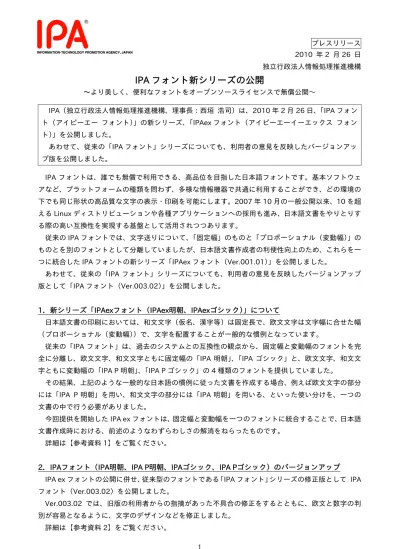
IPA フォント新シリーズの公開
〜より美しく、便利なフォントをオープンソースライセンスで無償公開〜 IPA(独立行政法人情報処理推進機構、理事長:西垣 浩司)は、2010 年 2 月 26 日、「IPA フォン ト(アイピーエー フォント)」の新シリーズ、「IPAex フォント(アイピーエーイーエックス フォン ト)」を公開しました。 あわせて、従来の「IPA フォント」シリーズについても、利用者の意見を反映したバージョンアッ プ版を公開しました。 IPA フォントは、誰でも無償で利用できる、高品位を目指した日本語フォントです。基本ソフトウェ アなど、プラットフォームの種類を問わず、多様な情報機器で共通に利用することができ、どの環境の 下でも同じ形状の高品質な文字の表示・印刷を可能にします。2007 年 10 月の一般公開以来、10 を超 える Linux ディストリビューションや各種アプリケーションへの採用も進み、日本語文書をやりとりす る際の高い互換性を実現する基盤として活用されつつあります。 従来の IPA フォントでは、文字送りについて、「固定幅」のものと「プロポーショナル(変動幅)」の ものとを別のフォントとして分離していましたが、日本語文書作成者の利便性向上のため、これらを一 つに統合した IPA フォントの新シリーズ「IPAex フォント(Ver.001.01)」を公開しました。あわせて、従来の「IPA フォント」シリーズについても、利用者の意見を反映したバージョンアップ 版として「IPA フォント(Ver.003.02)」を公開しました。 1.新シリーズ「IPAexフォント(IPAex明朝、IPAexゴシック)」について 日本語文書の印刷においては、和文文字(仮名、漢字等)は固定長で、欧文文字は文字幅に合せた幅 (プロポーショナル(変動幅))で、文字を配置することが一般的な慣例となっています。 従来の「IPA フォント」は、過去のシステムとの互換性の観点から、固定幅と変動幅のフォントを完 全に分離し、欧文文字、和文文字ともに固定幅の「IPA 明朝」、「IPA ゴシック」と、欧文文字、和文文 字ともに変動幅の「IPA P 明朝」、「IPA P ゴシック」の 4 種類のフォントを提供していました。 その結果、上記のような一般的な日本語の慣例に従った文書を作成する場合、例えば欧文文字の部分 には「IPA P 明朝」を用い、和文文字の部分には「IPA 明朝」を用いる、といった使い分けを、一つの 文書の中で行う必要がありました。 今回提供を開始した IPA ex フォントは、固定幅と変動幅を一つのフォントに統合することで、日本語 文書作成時における、前述のようなわずらわしさの解消をねらったものです。 詳細は【参考資料 1】をご覧ください。 2.IPAフォント(IPA明朝、IPA P明朝、IPAゴシック、IPA Pゴシック)のバージョンアップ IPA ex フォントの公開に併せ、従来型のフォントである「IPA フォント」シリーズの修正版として IPA フォント(Ver.003.02)を公開しました。
Ver.003.02 では、旧版の利用者からの指摘があった不具合の修正をするとともに、欧文と数字の判 別が容易となるように、文字のデザインなどを修正しました。
IPAexフォントシリーズについて
特徴:
(1)固定幅文字とプロポーショナル(変動幅)文字の統合 「IPA明朝・IPA P明朝」および「IPAゴシック・IPA Pゴシック」をそれぞれ一つのフォントに統 合した「IPAex明朝」、「IPAexゴシック」を新規に開発しました。和文文字(仮名、約物4、漢字) は固定幅で、欧文文字は文字幅に合せた幅(変動幅)を基本としたドキュメント用日本語フォント の標準的な実装を行いました。 欧文=変動幅 仮名=変動幅 約物=変動幅+固定幅 漢字=固定幅 記号=変動幅+固定幅 IPA P明朝/ゴシック 欧文=固定幅 仮名=固定幅 約物=固定幅 漢字=固定幅 記号=変動幅+固定幅 IPA 明朝/ゴシック 欧文=変動幅 仮名=固定幅 約物=固定幅 漢字=固定幅 記号=原則固定幅 IPAex 明朝/ゴシック3 Open Type Font: TrueType 形式を発展させたフォントフォーマットであり、アドビシステムズ社、マイクロソフト 社が共同で設計し、アップルコンピュータ社が賛同する形で開発・制定され、公開されています。Linux、Windows、 Mac OS X 等の異なるプラットフォーム間での互換性が高いデファクトスタンダードのフォントフォーマットです。 4 句点“。”読点“、”括弧“(”といった記号等。
① IPAex 明朝の仮名デザイン、IPAex ゴシックの濁点のデザインを全面見直し ② 数学記号全般を視覚的に違和感のないようにデザイン統一
③ 一部の固定幅(全角サイズ)でデザインされた欧文グリフを変動幅に設定 ④ 矢印、幾何学模様、その他の記号類などを固定幅(全角サイズ)に合せて最適化
⑤ U+0361(COMBINING DOUBLE INVERTED BREVE)と U+203F(UNDERTIE)の修正。こ の 2 つの字形は、標準的な和文書体と文字送り幅が異なっていたため、適切なデザインに修 正しました。
(3)一部キャラクタの仕様変更(円記号、バックスラッシュ)
「IPA フォント」では、U+005C と U+00A5 の双方に重複して円記号“¥”を割り当てています。 しかし、「IPAex フォント」では、多様なプラットフォームでの使用を前提とした国際的な相互運用 性を重視し、Unicode の仕様通り U+005C にバックスラッシュ“ ”、U+00A5 に円記号“¥”を 割り当てました。
(4)JIS0213:2004 制定時に字体変更された文字の旧字体を異体字として収容
IPAexフォントは、JIS X 0213:2000 からJIS X0213:2004 に規格が更新された際に変更された字 形について、新旧双方の字形を、IVS(Ideographic Variation Sequence)方式5で収録しています。対
象文字数は 171 文字です。
(5)使用頻度の高い記号類を新規作成して収録
Unicode の CJK Symbols、CJK Compatibility Symbols、Enclosed CJK における使用頻度の高い 文字(AJ1-6 に存在する文字)、202 文字を新規に収録しました。
IPAフォントシリーズについて
今回の修正点について:
(1) ヒント情報の付加(IPAex フォント含む全ての IPA フォント) 小さなピクセルサイズの文字表示品質を向上するために、ヒント情報を付加しました。 ヒント情報とは、アウトラインフォントを低解像度のモニターなどに出力する際、小さい文字が潰れ たり、線幅が不ぞろいになったりするのを補正するためにフォント内に設定する情報のことです。 (2) ひらがなやカタカナに濁点や半濁点を付加した場合の処理情報の追加 例えば、 などの置換情報を追加し、より簡易に多様な入力・表現ができるようにしました。 (3) IPA ゴシックの半角欧文デザイン変更 プログラミング時やデータの表示などにとって、より便利なものとなるよう、欧文と数字の違 いがわかるようにキャラクタデザインを修正しました。 5②拡張子の変更(otf から ttf)
IPA フォントの歴史
• 2004 年: IPA フォントの試行的公開を開始(IPA フォント Ver.1)
– フォントの用途を「IPA の支援するプロジェクトによって開発されたソフトウェアを活用するた め」と限定し、同ソフトウェアをフォントに同梱することを配布条件とした。 – 明朝(等幅、プロポーショナル)、ゴシック(等幅、プロポーショナル)、UI ゴシック の計 5 書 体 – JIS X0208 に準拠した 7,000 文字/書体 – TrueType フォーマット – OSS を含む多様なプラットフォームで共通に活用可能な無償の唯一の高品位日本語フォントとし て広く認知される。
• 2007 年 10 月:IPA フォントの一般公開を開始 (IPA フォント Ver.2) – 用途限定無し、改変不可のライセンス – 明朝(等幅、プロポーショナル)、ゴシック(等幅、プロポーショナル)、UI ゴシック の計 5 書 体 – 文字を追加し、最新の JIS 規格 JIS X0213:2004 に準拠した約 11,000 文字/書体 – TrueType フォーマット – 一般利用者の他、特許庁などでの活用も進む。
• 2009 年 4 月 20 日:新ライセンスの下で IPA フォント新版の配布開始(IPA フォント Ver.3) – 用途限定無し、改変可能のライセンス – 明朝(等幅、プロポーショナル)、ゴシック(等幅、プロポーショナル)の計 4 書体 – JIS 規格 JIS X0213:2004 に準拠した約 11,000 文字/書体 – Open Type フォーマット – OSS オープン・ラボにフォント開発ツールの利用環境を整備 ・2010 年 2 月 26 日:IPAex フォントの配布開始 – IPA フォント(Ver.003.02)、リリース – IPAex フォントの配布開始 7
■IPAex 明朝 11 美しい⽂字で楽しいソフトウェア開発
24 美しい⽂字で楽しいソフトウェア
72 美しい⽂
■IPAex ゴシック 11 美しい⽂字で楽しいソフトウェア開発24 美しい⽂字で楽しいソフトウェア
72 美しい⽂
IPA フォント(Ver.3)印刷⾒本 ■IPA 明朝 11 美しい文字で楽しいソフトウェア開発24 美しい文字で楽しいソフトウェア開
72 美しい文
89 ■IPA P 明朝 11 美しい文字で楽しいソフトウェア開発